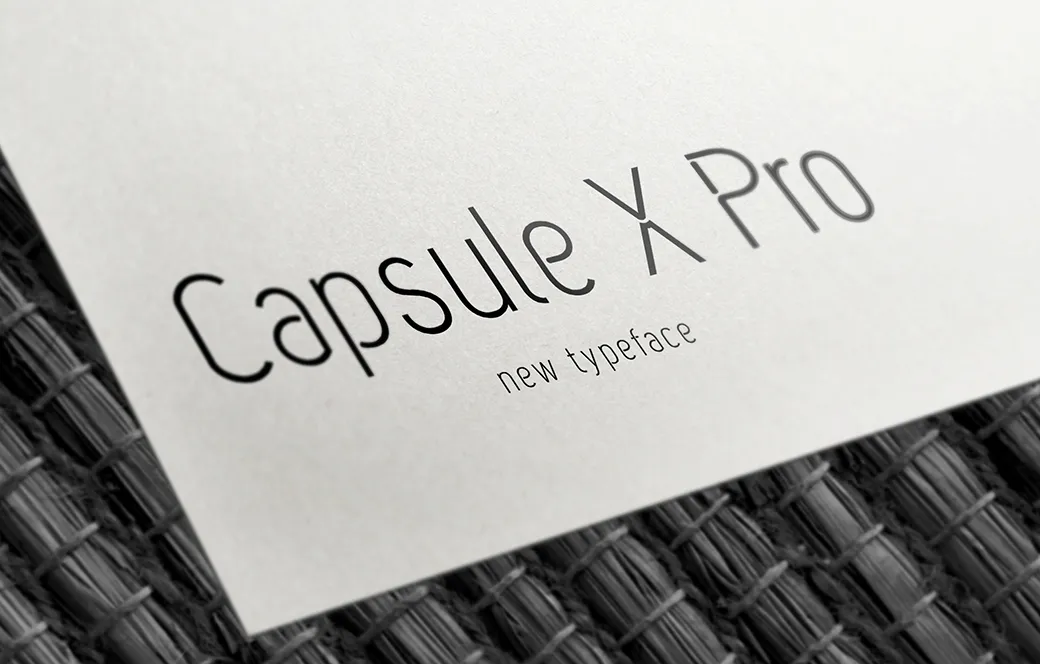
A Capsule X Pro Typeface é uma escolha perfeita para quem busca uma fonte moderna e elegante no estilo sans serif. Com linhas arredondadas e linhas leves, essa fonte garante um design limpo e profissional sem perder o charme da tipografia mais minimalista. Criada pelo designer Hamilton, a Capsule X Pro é perfeita para uso em aplicativos de e-mail, sites corporativos ou qualquer projeto que busque uma expressão sofisticada. Suas linhas finas e precisas dão ao texto um ar moderno e minimalista, tornando-a ideal para ambientes digitais contemporâneos. Com o seu design agradável, fácil de ler e versátil, esta fonte irá fazer sua marca se destacar no ambiente digital. A Capsule X Pro é uma ótima escolha para aqueles que desejam um arco-íris digital fresco e clean sem perder seu toque personalizado ou a qualidade de impressão da tipografia serifada.